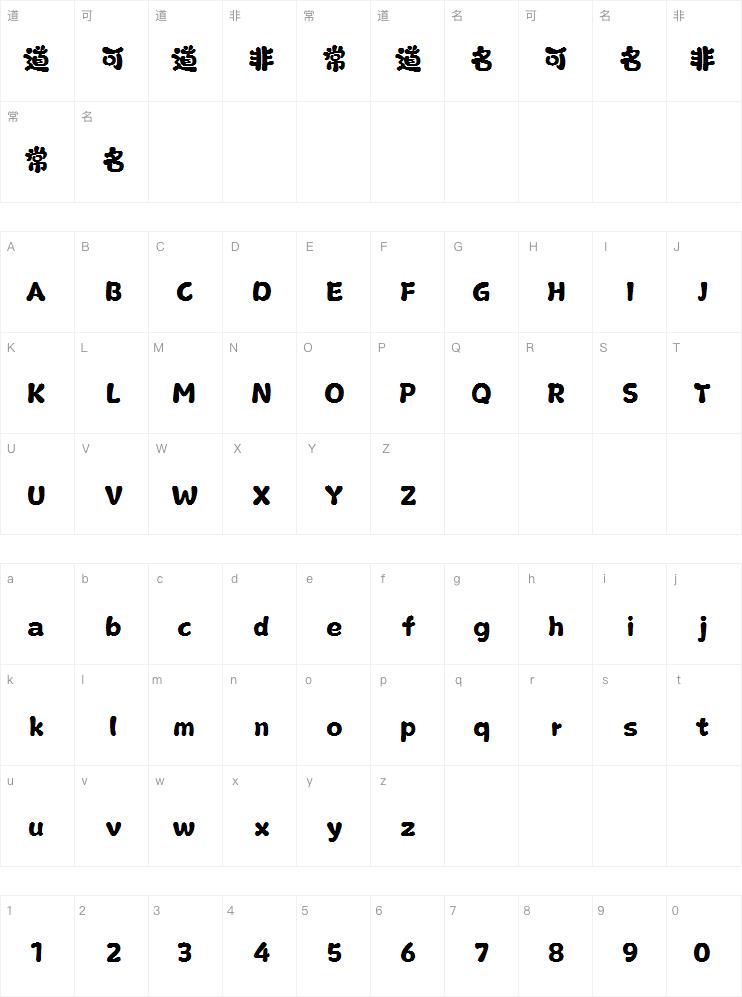
山海小奶油w
山海小奶油,是一款全新的字体,包含汉字9169个,符号200+个。该字体是一款卡通风字体,该字体字形灵动多变,童趣可爱,整体笔触圆润,每个笔画似奶油般软糯,同时结构活泼清新,造型生动有趣,具有灵活的适用性,天真俏皮又不失时尚感。该字体各个字的大小随字形的不同而呈现不同的大小,但是在变化中寻求平衡,在多变的同时有保持整体均衡匀称,使得整个字体更具有温度感和节奏感,整体笔触圆润,灵动笔画贯穿笔画始终,内涵丰富,弧度柔和,撇笔平缓舒展,尽显俏皮灵动。